美术字体设计是互联网世界中比较流行的字体,让你在社交媒体上,或者是网络世界里都有一款非常精致的字体来凸显你的艺术气质,就是根据不同客户的需求,来设计出不同的美术字体来供多个客户选择。当你看到一张图片时。想要知道图片字体是什么的话可以通过字体识别功能来搜字体。
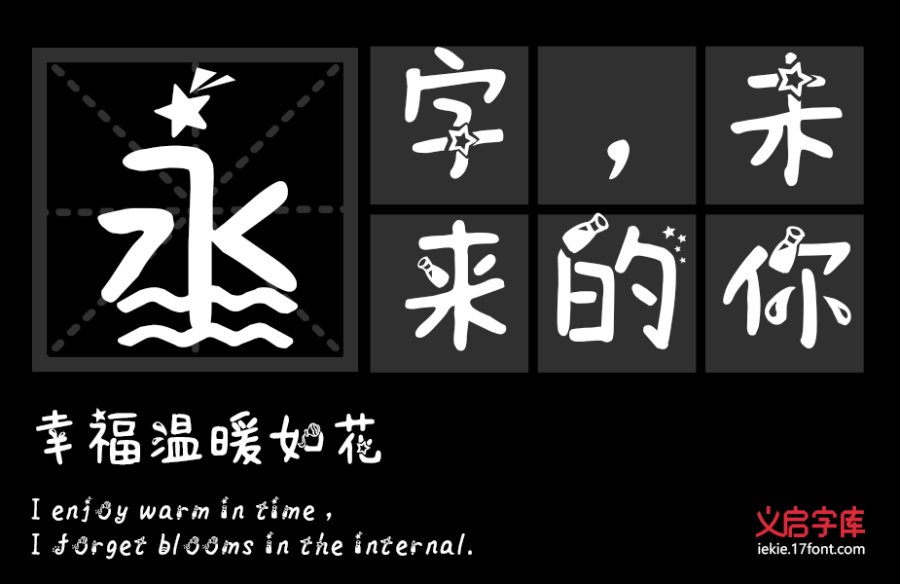
在拥有众多的年轻设计师的字体视界中,分别对不同的客户展开调查,设计出符合每个人个性及大众审美共性的字体,是他们的追求,其设计理念来源于每一个不同客户的要求,在六一儿童节你需要发朋友圈时,是不是想拥有一款特别独特的、特别卡哇伊的字体,那么,字体视界中义启字库的义启熊孩子体就特别符合你的要求,设计师也是根据儿童这一理念来设计出的。
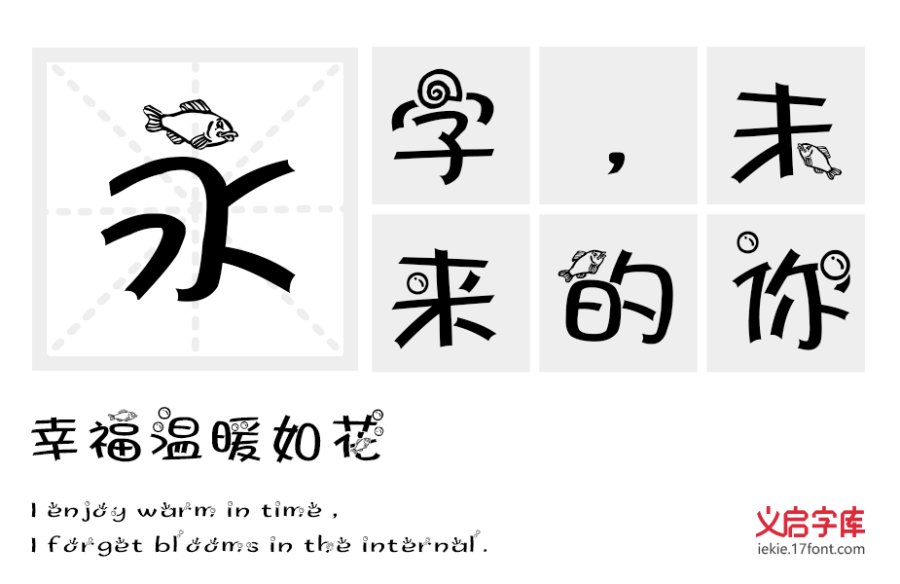
字体视界的美术字体设计在全网拥有非常多的粉丝,因为字体视界拥有*多的,海量的字库来供客户选择,不管是萌萌的美少女,还是御姐范的女神,或者是书法爱好者,都能选出适合自己的美术字体设计。特别是根据不同星座来设计出的美术字体更是受到了广大客户的喜爱,不管是天蝎座字体的神秘,还是处女座字体的冷淡,或者是白羊座字体的热情,都被设计师团队设计的淋淋尽致,显现每一个客户的个性。更多图片字体可通过搜字体网进行搜索查找字体哦。